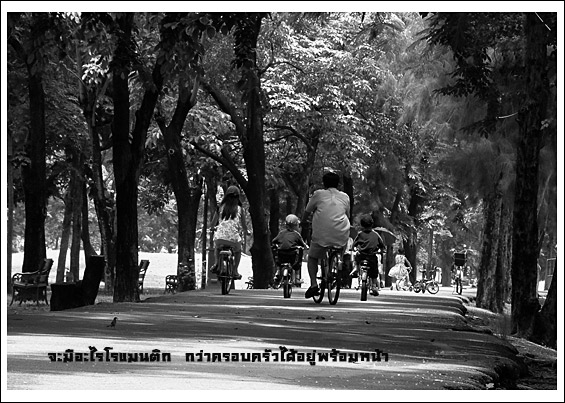
เห็นแล้วสะเทือนใจ นี่แหละศิลปะ
แย่แล้ว มุกลอยลม ไม่มีใครมาตบมุกเลย
ดูไม่รู้เรื่อง
โอเคงั้นตูช่วย
นั่นมันรถติด ไม่ใช่โรแมนติก
อ๋อ!!!
อ๊อออ
เอ้า
ฮากันหน่อย
ส่งงานที่สองครับ
ภาพสวย แต่ฟอนต์หนักหน่วงไปหน่อยนะครับ
เหมือนได้ยินเสียงพากษ์ทีวีแชมเปี้ยนน่ะ
ขอบคุณลุงอ๋าห์ที่ช่วยติชมครับ
จะดีกว่านี้ถ้าใช้ฟอนต์เล่นรุนแรงครับ
ผมว่าทำเป็นรูปเปล่า ๆ ไม่ต้องมีข้อความดีกว่าครับ
เว้นที่ว่างให้คนดูได้คิดเอง
ผมว่าทำเป็นรูปเปล่า ๆ ไม่ต้องมีข้อความดีกว่าครับ
เว้นที่ว่างให้คนดูได้คิดเอง
กลัวคนดูจะคิดไปเป็นอื่น เดี๋ยวจะไม่เข้าโจทย์ครับ
จะดีกว่านี้ถ้าใช้ฟอนต์เล่นรุนแรงครับ
ป๋าชอบรุนแรงเหรอครับ
ชอบแบบไม่มีตัวอักษรเหมือนกันครับ
ถ้าจะอธิบายก็เขียนไว้นอกรูป จะดูเบานุ่มกว่า
โรแมนติก = รถมันติด ออกเสียงคล้ายๆกัน (แบบไทยๆด้วยนะ)